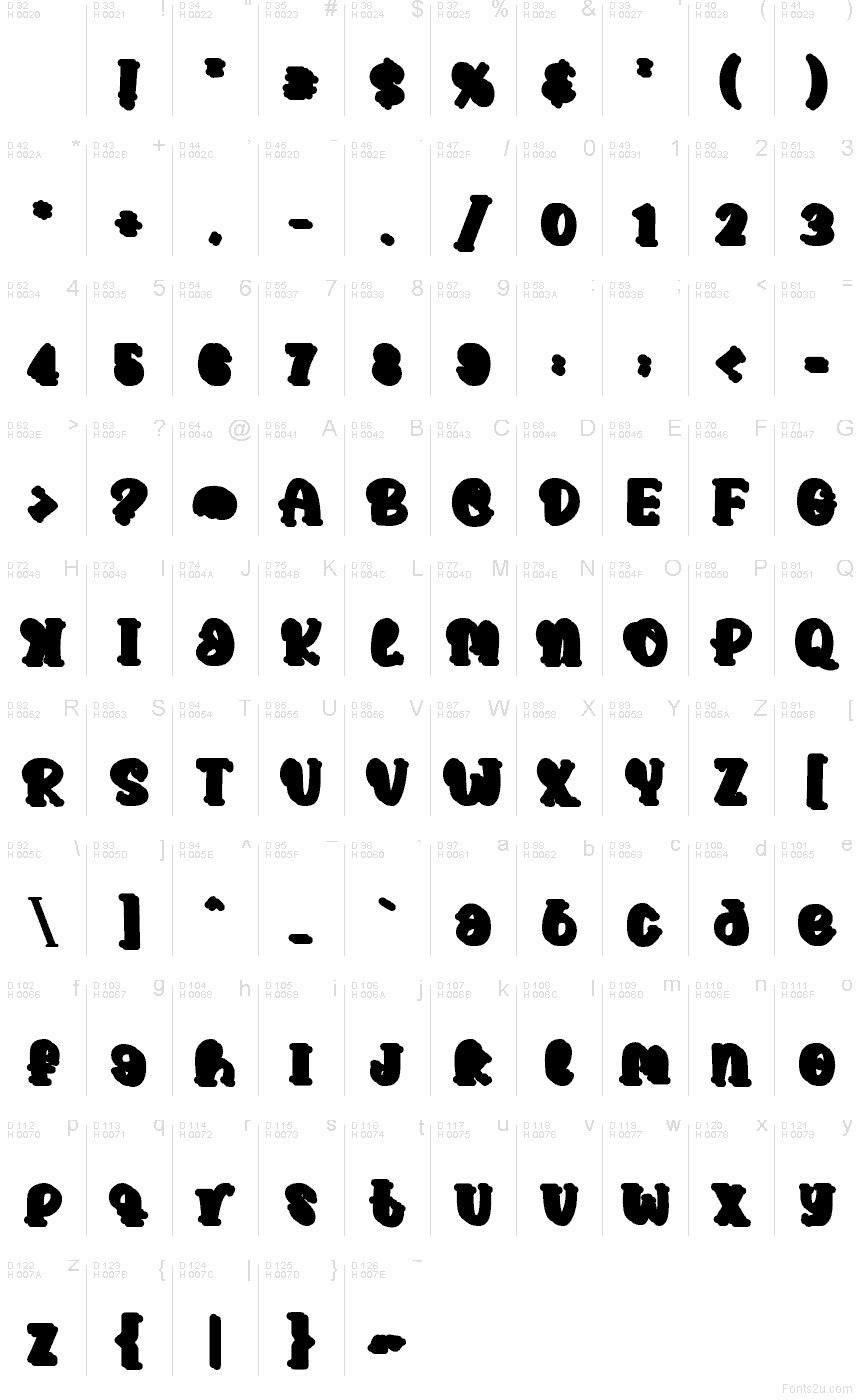
Halo Domas Shadow
Halo Domas Shadow je bezplatné, dekorativní písmo od studia Mabhal Studio, kterému dominují nadýchané tvary písmen a hravé zahnuté detaily. Jeho tučné a těsně poskládané znaky vytvářejí jemný, skákavý rytmus, zatímco přehnané křivky dodávají krátkým slovům živý, téměř kreslený výraz.
Použijte toto bezplatné písmo na plakáty, obaly alb, festivalovou grafiku, hravé obaly a energické titulky. Skvěle se hodí také pro krátké nadpisy, kde mají široké tvary a zakroucené detaily dostatek prostoru k tomu, aby vytvořily silný vizuální dojem.